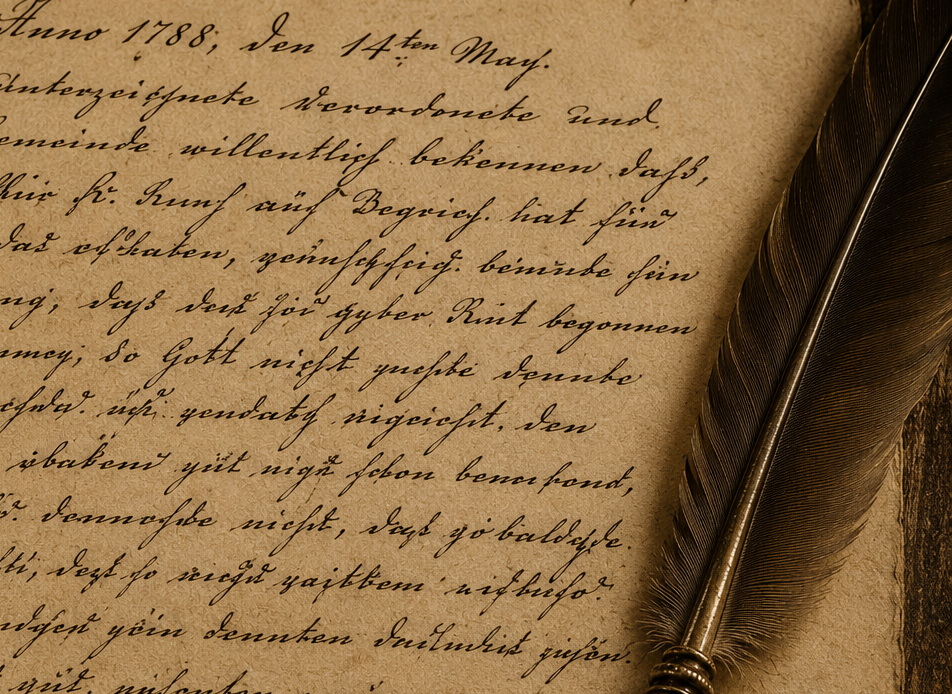
Die Handschrift eines Menschen ist unverwechselbar und vermittelt Persönlichkeit. Kein Mensch schreibt exakt wie ein anderer. Rhythmus, Druck, Neigung, Linienführung und Buchstabenformen entstehen aus der persönlichen Motorik und entwickeln sich über viele Jahre. Die persönlichen Stile erschweren mir einerseits beim Übersetzern die Arbeit – die Texte bedürfen einer längeren Einlesezeit, um sich an die Handschrift und die Textmelodie zu gewöhnen. Andererseits aber bewahrt jedes erhaltene Schriftstück ein Stück menschlicher Erinnerung und ist es wert, entschlüsselt zu werden.
Verzierungen, Initialen und kalligraphische Gestaltung machen viele historische Schriftstücke zu einzigartigen Kunstwerken, die sich nicht reproduzieren lassen, ohne einen Teil ihrer ursprünglichen Ausstrahlung zu verlieren. Während ein digitaler Text irgendwann im Irrgarten des Internets verschwindet, kann ein gut erhaltenes handschriftliches Dokument Jahrhunderte überdauern und bleibt als authentisches Original erhalten. Es bildet eine verlässliche Quelle für kommende Generationen und schafft eine direkte Verbindung zur Vergangenheit.
Eine kunstvoll ausgeführte Handschrift war einst Ausdruck von Bildung und Wohlstand, von Autorität und kultureller Identität. Historische Handschriften geben Einblicke in Sprache, Schriftentwicklung und in das tägliche Leben vergangener Jahrhunderte. Heute hat ein schön geschriebener Text beinahe eine symbolische Bedeutung und erinnert uns daran, dass wahre Qualität Zeit und Hingabe erfordert.
Die Handschrift verliert heute zunehmend ihren festen Platz im täglichen Leben, obwohl zahlreiche wissenschaftliche Untersuchungen zeigen, dass Schreiben Konzentration und Aufmerksamkeit fördert und das Lernen unterstützt. Der langsamere Schreibprozess gibt dem Gehirn Zeit, Ideen zu entwickeln und Gedanken miteinander zu verknüpfen. Wer Inhalte mit der Hand notiert, setzt sich automatisch stärker mit ihnen auseinander, ordnet Gedanken und fasst Informationen zusammen. Dies verbessert das Verständnis und erleichtert das langfristige Erinnern.
Zudem: Handschrift entschleunigt. Sie fördert bewusstes Denken und bewahrt eine Kulturtechnik, die den Menschen über Jahrhunderte begleitet hat. Handschrift ist nicht nur ein Werkzeug zum Schreiben – sie ist Ausdruck von Identität, Kreativität und geistiger Auseinandersetzung mit der Welt.
Ein handgeschriebener Brief oder eine persönliche Widmung vermitteln Nähe und Wertschätzung, welche eine maschinell erzeugter Text nur selten erreicht. Gerade weil jede Zeile sichtbar von einer menschlichen Hand geschaffen wurde, entsteht eine unmittelbare Verbindung zwischen Verfasser und Leser.